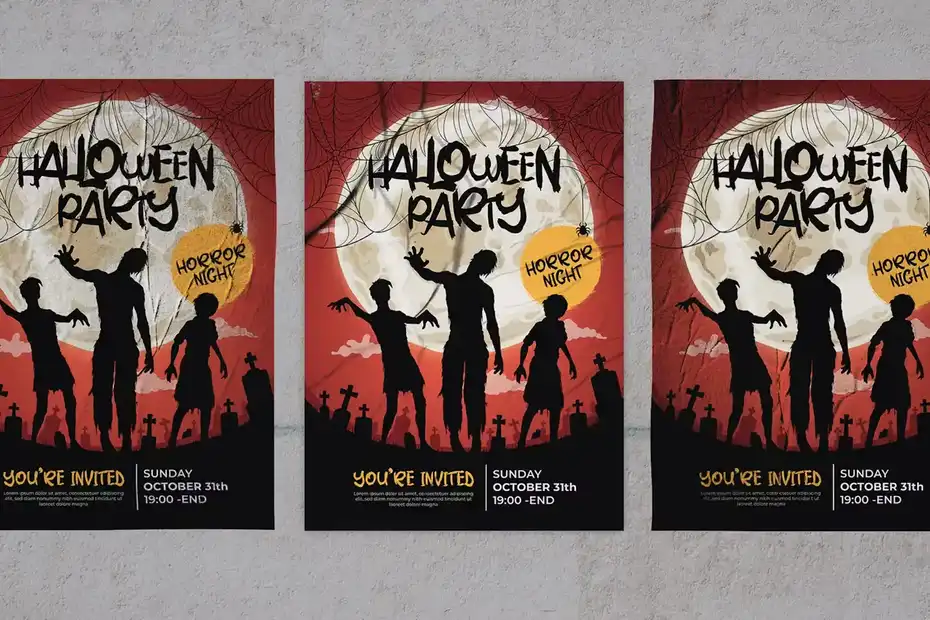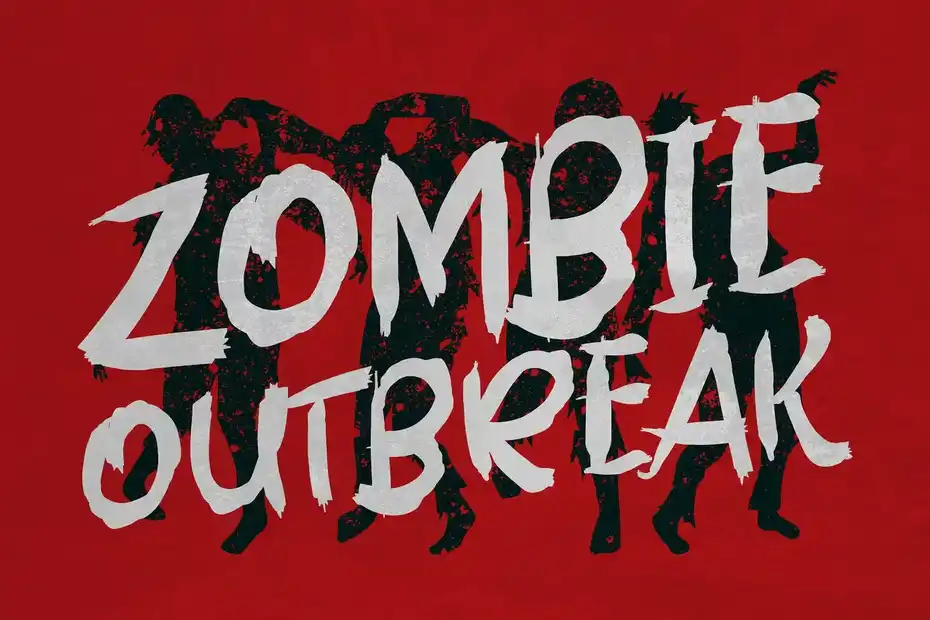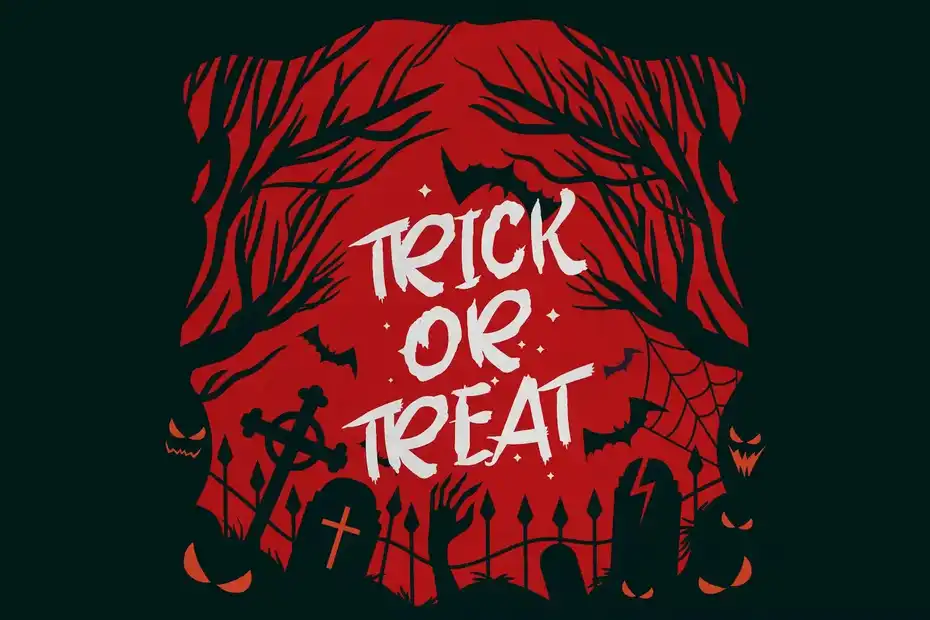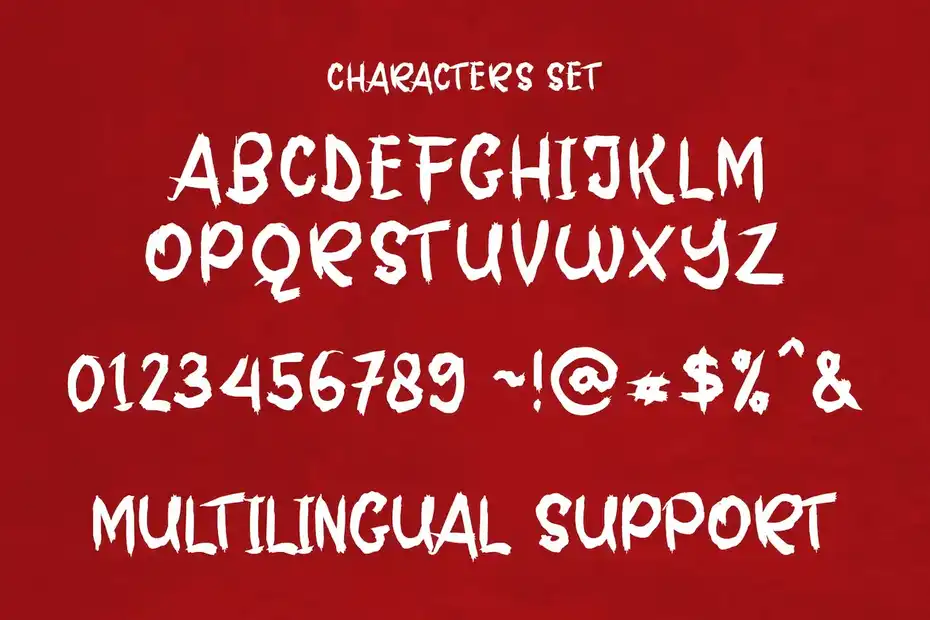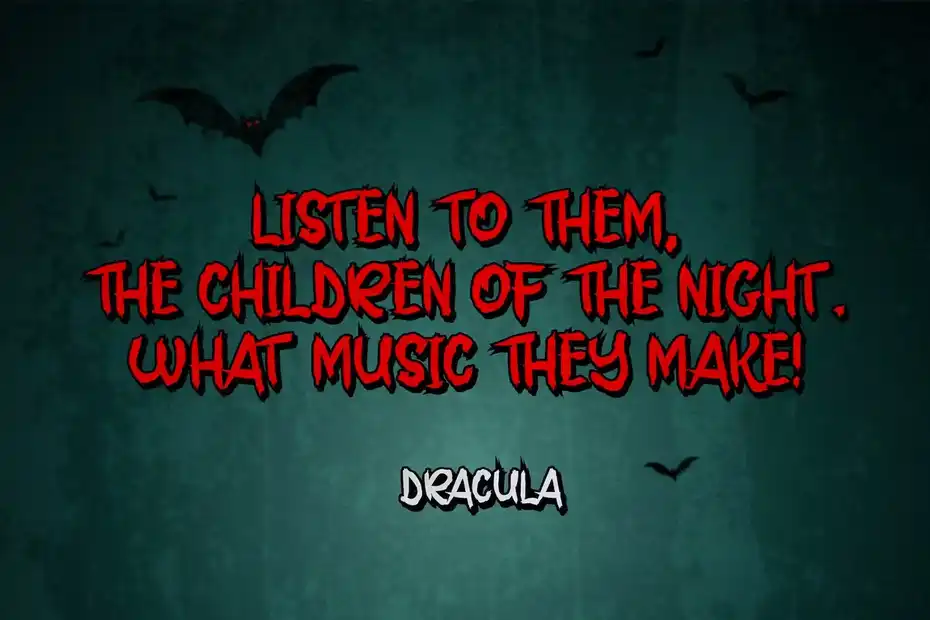
دانلود فونت ترسناک هالووین Night Beats – Scary Halloween Font
دانلود فونت ترسناک هالووین Night Beats – Scary Halloween Font : این مجموعه شامل یک فونت انگلیسی ترسناک است که برای هالووین، نقل قول، لوگو، برچسب، بسته بندی و غیره مناسب میباشد. برای مشاده فونت های ترسناک بیشتر می توانید بخش فونت انگلیسی ترسناک را در سیجی کوک مشاهده کنید.
• عنوان مجموعه: Night Beats – Scary Halloween Font